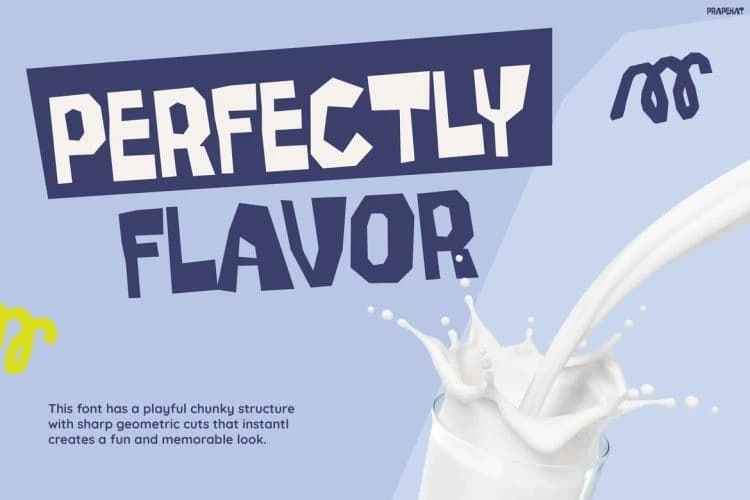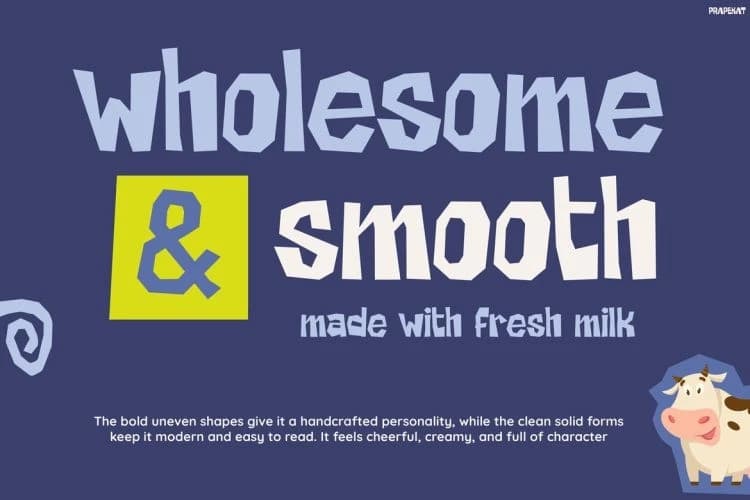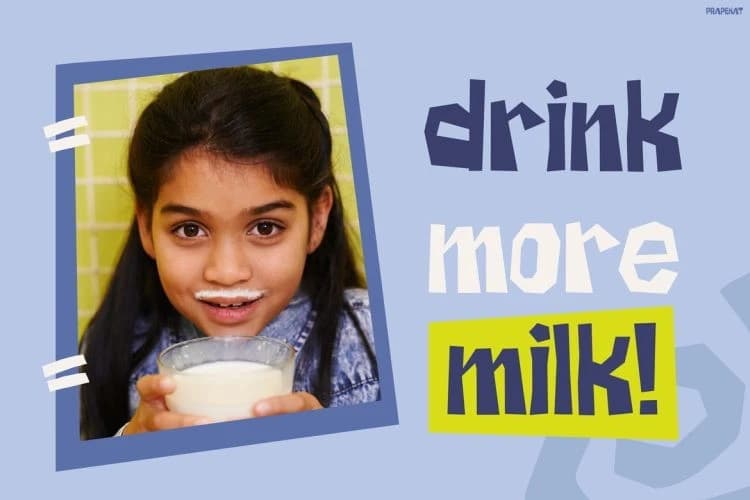
Prapekat Görüntü Yazı Tipi
Prapekat Display Font, her projeyi daha canlı, daha renkli ve kişilik dolu hissettirmek için tasarlanmış cesur ve eğlenceli bir gösteri yazı tipidir. Çizgi film grafikleri, retro atıştırmalık ambalajları, süt ürünleri markalaşması ve neşeli çocuk görsellerinden ilham alır.
Prapekat Display Font, her projeyi daha canlı, daha renkli ve kişiliğiyle dolu hissettirmek için tasarlanmış cesur ve eğlenceli bir gösterim yazı tipidir. Çizgi film grafikleri, retro atıştırmalık ambalajları, süt ürünleri markalaşması ve neşeli çocuk görsellerinden ilham alınmıştır.